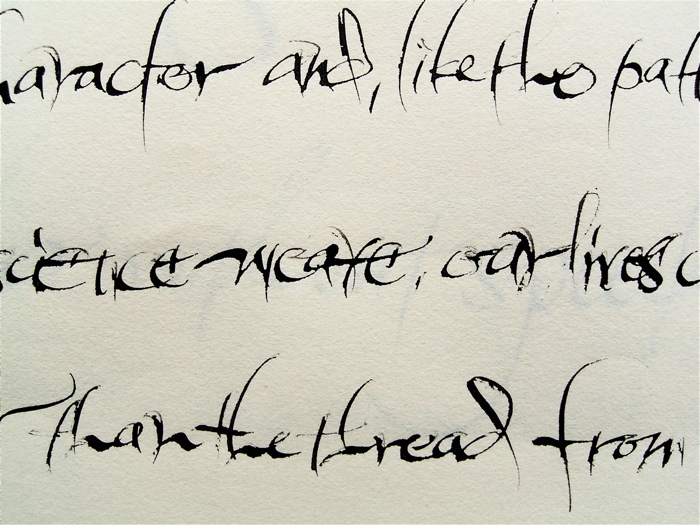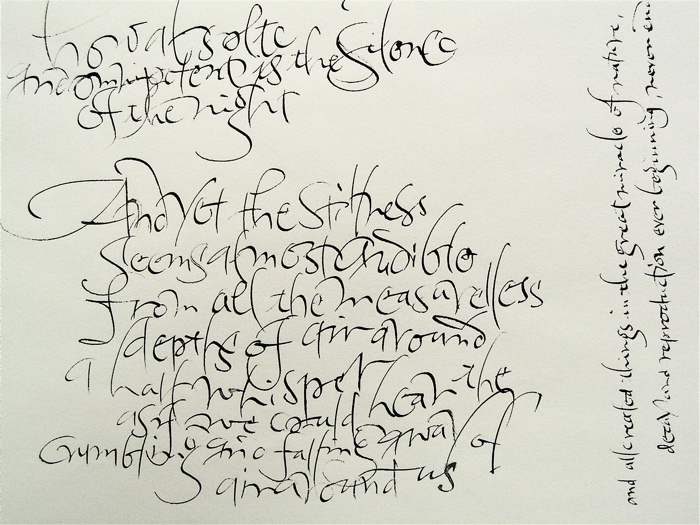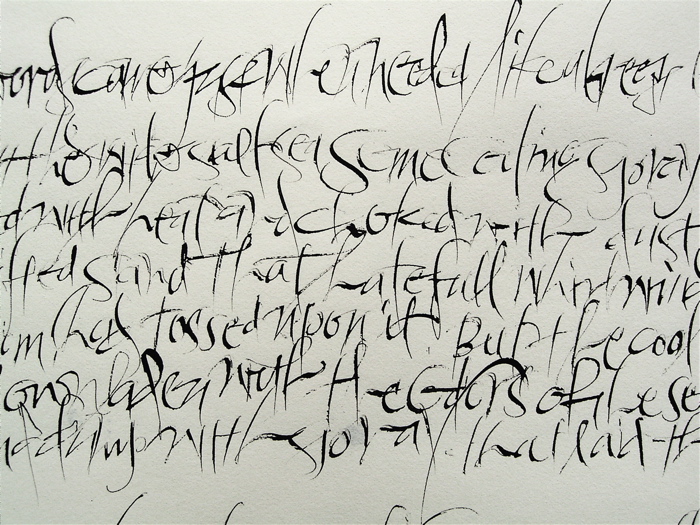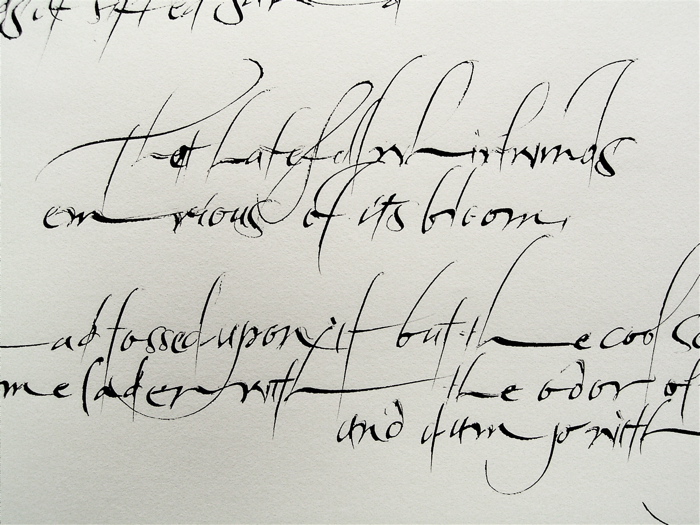
イタリック体の練習
昨日はArrighiに関してバカバカしいことを書いたので、や〜ん、ライティングマスターの神様がへそ曲げちゃったらどうしよう、とちょっと心配になり、そうだ、心も新たに練習しようと思って少し文字を書いてみました。
こういう動きのあるイタリック体の文字を書くときには、ブラウゼのペン先が何と言ってもひっかからずに書きやすいのですが、わざとひっかかるミッチェルで書いたらどうなるかを以前試した事があって、それをもう一度書いてみたのです。
紙もざらざらしているし、ミッチェルは角がシャープでひっかかるし、スピードを早く書く事はとても困難!ガリガリくんです。
でも書き続けて行くと、こんな感じに面白い線が出てきました。
雑にならない様、線の美しさを意識して書くべし、と肝に銘じて練習しますが、なかなかそれはとっても難しい。
どうしても雑になってしまいますよね。ここが練習のしどころ、課題、必須事項です。
でも試してみる価値はありました。文字の種類や書き方によって道具を選ばなければなりませんが、敢えて使いにくい道具でやってみる。そうすると何か新しい発見ができるかもしれませんね。
やはりブラウゼだとひっかかりがなく、とても書きやすいです。(でもあとから見るとなんだかウルサイ感じ。フワフワではなく、うじゃうじゃになってしまった・・・・)
さてさて、美しい文字を書くにはこれからも練習あるのみ!きれいでオーガニックな線を持ち、美しく動きがあり個性が存在するイタリック体を目指しま〜す。
Mojitor-sさんとレヴェルの差はあれ同じような事してます。先週末にSharon ZeuginさんのWork Shop " The Journal is the Destination "を受けました。彼女のオーガニックで美しい文字にずっと憧れていた私はそのデモンストレーションにびっくり!ものすごく早いんです。小文字のa to zは3秒くらいで。しかもため息が出るほど美しい。”こんなに早く書く人は初めて見た”と参加の経験豊かなカリ人さん達も感嘆。Sharonさんはミッチェル#6が愛用。いつも次のストロークの動きと全体の空間を読みながら書くそうです。私もミッチェル#6で練習したけど、やっぱりひっかかるし、練習あるのみという感じです。ちなみにSharonさんは安いスケッチブックのスムーズな紙がお気に入りだそうです。
Sharon ZeuginさんのWork Shopに参加されんですね!とても羨ましいです。
以前Annie Cicaleのワークショップを受けた時、ちょうど彼女がそのWSの前にSharon のクラスを受講して来たと言っていろいろと見せてくれた事がありました。
墨流しを使った縦長の下地に書いたものが印象的でした。紙の端をすべて墨で染めてあって、素敵でした。
私もものすごく早く書くデモを見てみたい〜!小文字のa to zが3秒くらいってどんな速さでしょう・・・・。しかもミッチェルの#6を使うなんて・・・信じられません。
よ〜〜〜く考えてみたら,3秒ってのはちょっと無理? あっという間だったので、それくらい速く感じたという事で!